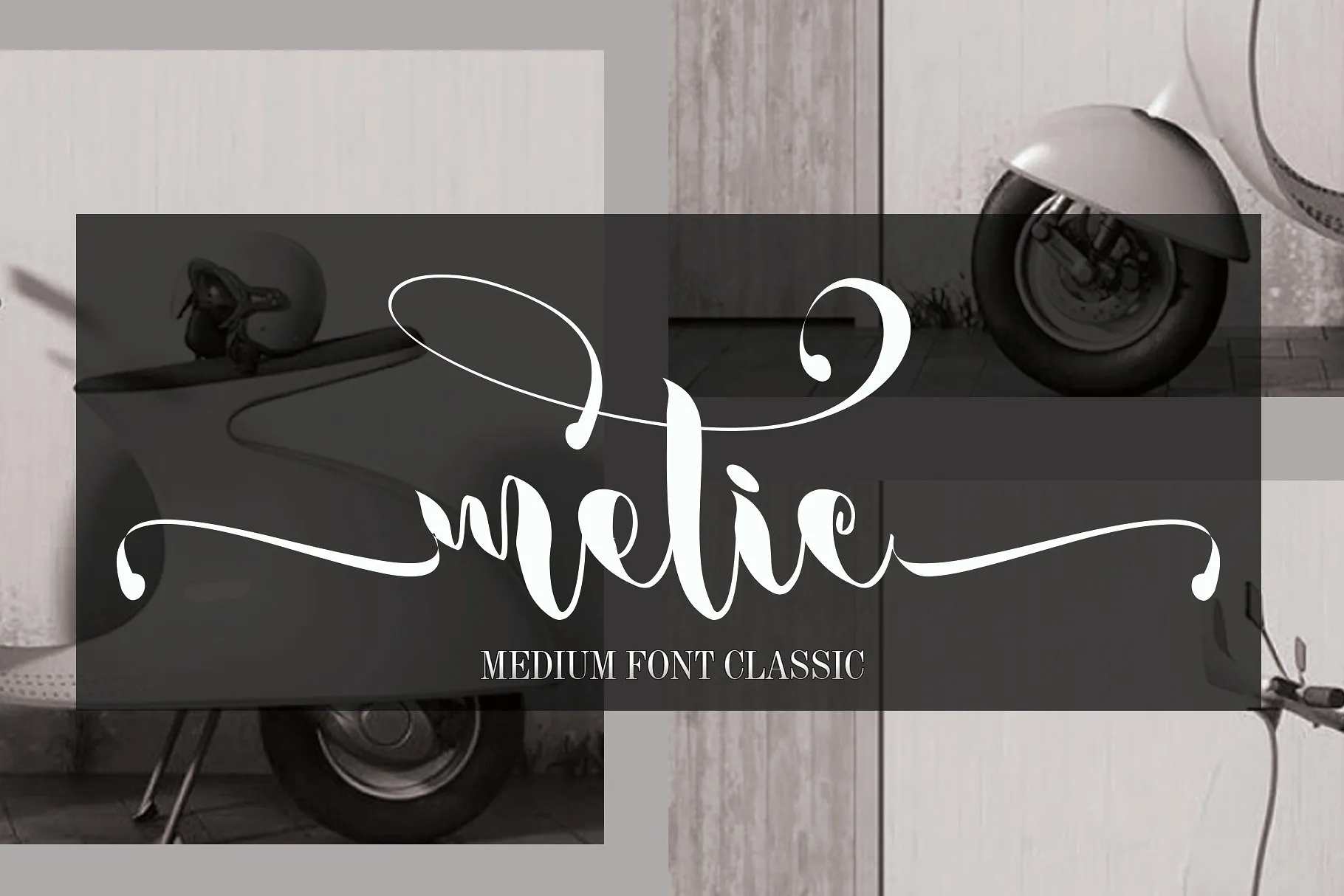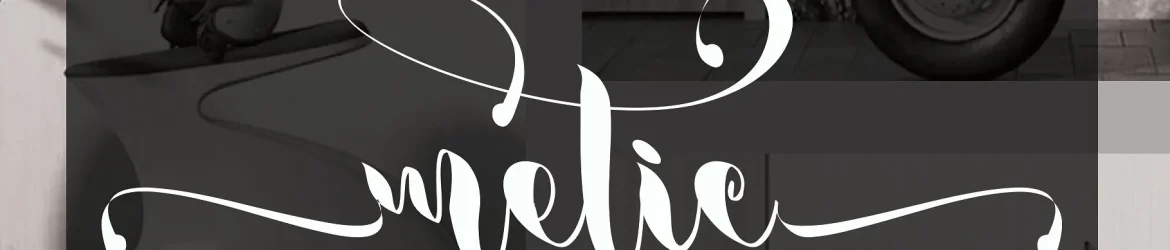
Metic Calligraphy Font – Download Grátis
Essa é uma bela oportunidade para adicionar um toque refinado à sua próxima projetada ou design. A Metic Calligraphy Font apresenta uma elegância clássica, trazendo ao seu trabalho um ar de sofisticação e estilo moderno. Esta fonte média é perfeitamente adequada para ambientes mais formais, mas também é flexível o suficiente para se adaptar a várias necessidades de design em eventos especiais ou simplesmente aqueles momentos em que você deseja adicionar um charme especial à sua tipografia. Como Designer C00zona criou esta fonte exclusiva e única, está ao seu alcance personalizar diferentes elementos do seu design sem comprometer o estilo elegante da Metic Calligraphy Font. Sua funcionalidade abrange a criação de cartões de cumprimentos personalizados ou até mesmo designs de livros de registro, oferecendo uma variedade inigualável para seu próximo projeto. Descubra por si mesmo como esta fonte pode se adaptar às suas necessidades individuais e transformá-la em algo único e memorável.